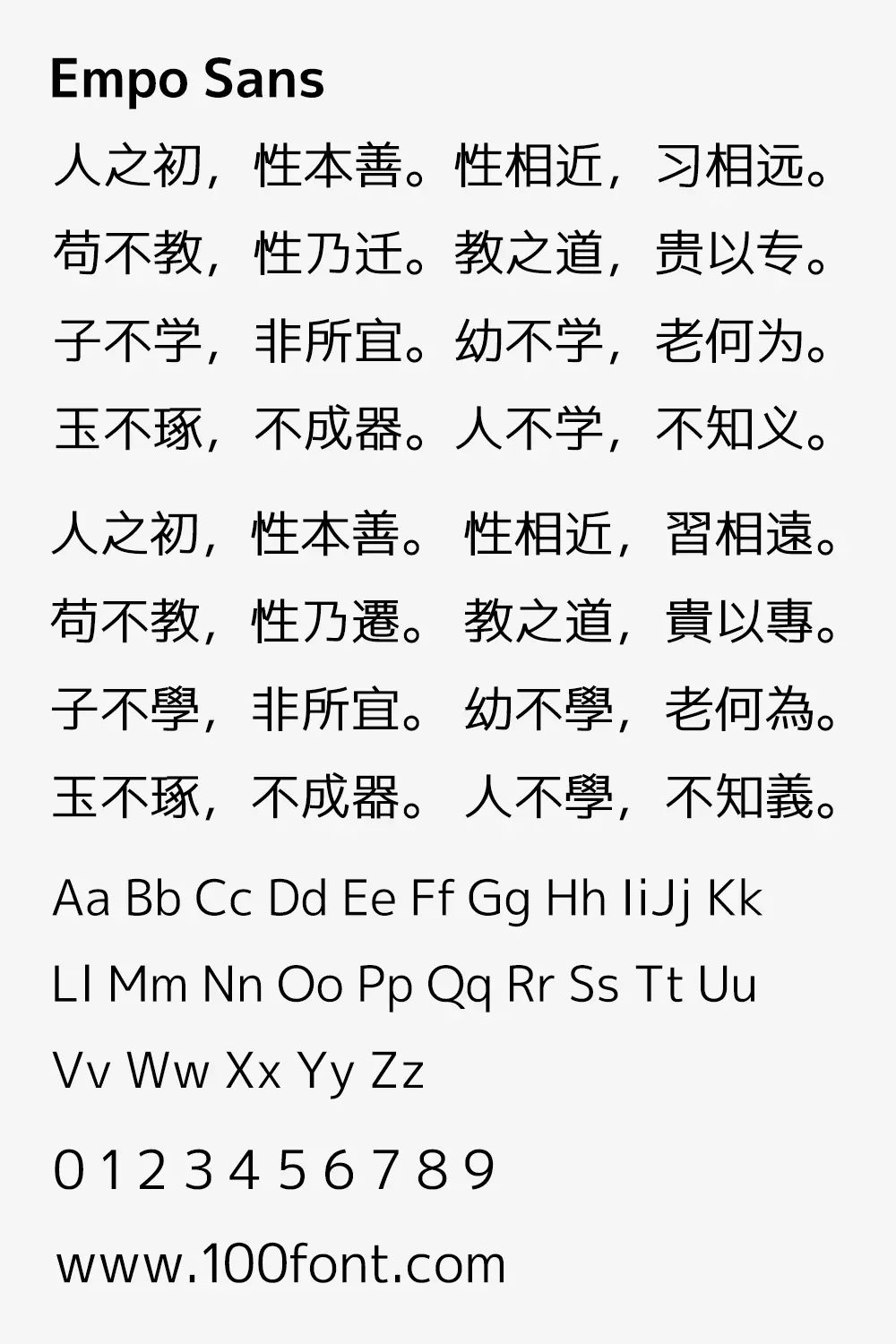
Empo Sans 是一個基於 M+ Fonts(新版 · 舊版)擴展的簡體中文字體,做工很糙。Empo Sans 包括了細體(light)、常規體(regular)和粗體(bold)三種粗細。
漢字部分完成度
各種粗細的完成度如下:
● 細體
GB/T 2312 一級字表:全部補完
GB/T 2312 二級字表:補做了一小部分
原版 M+ Fonts 已有的,但不在 GB/T 2312 範圍內的漢字:其字形都做了調整
除以上外,在 GB/T 2312 範圍內但沒有補完的漢字,暫時使用思源黑體 CN Light 進行填充
● 粗體
原版 M+ Fonts 已有的,且字型與大陸新字形一致的:已基本粘貼完
原版 M+ Fonts 沒有的,但在 GB/T 2312 範圍內的:補做了一小部分
除以上外,在 GB/T 2312 範圍內但沒有補完的漢字,以及原版 M+ Fonts 已有但字型與大陸新字形不一致的,暫時使用思源黑體 CN Bold 進行填充
● 常規體
細體當中已經補完的漢字:直接將細體作橫向 15 個單位,縱向 10 個單位的算法加粗(筆畫較多的漢字會適當減小加粗的程度)
細體當中還沒補完的漢字:暫時使用思源黑體 CN Light 進行填充 (不是用的 Regular,所以常規體中沒做的字會比已經做好的字要細)
因為常規體是用算法加粗生成的,所以觀感上會比較差
西文和數字部分
Empo Sans 的西文和數字部分的字母是原版 M+ 1p 和 2p 的混合:
● B、D、P、R 等帶有半圓弧部件的字母來自 1p (1p 裡面的這類字母的半圓弧起筆和落筆有一定角度,不是水平的,與 Myriad 字體有些類似)
● 3、y 等字符來自 2p
● 1、f、t 這幾個字符比原版的 M+ 要窄一些
假名部分
Empo Sans 的假名來自原版 M+ 2p。